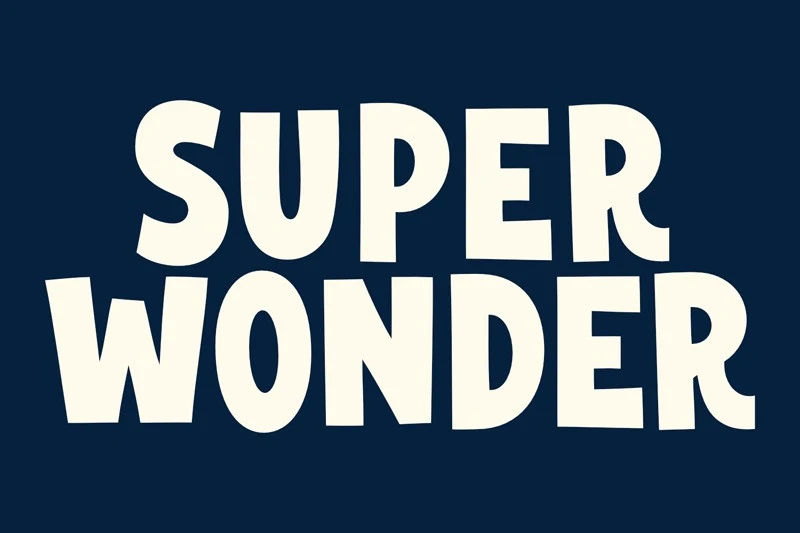
Super Wonder Font
Super Wonder Font, herhangi bir tasarıma eğlenceli ve canlı bir kişilik katması için tasarlanmış, çizgi film tarzı ve göz alıcı bir gösterim yazı tipidir. Kalın, yuvarlak hatlı ve hafif düzensiz harf biçimleriyle oyunbaz ve enerjik bir görünüm yaratır.
Super Wonder Font, herhangi bir tasarıma eğlenceli ve canlı bir kişilik kazandırmak için tasarlanmış, oyuncu ve dikkat çekici karikatür stilinde bir gösteri yazı tipidir. Kalın, yuvarlak hatlı ve biraz düzensiz harf biçimlerine sahip olan bu yazı tipi, büyüleyici ve enerjik bir görünüm yaratır